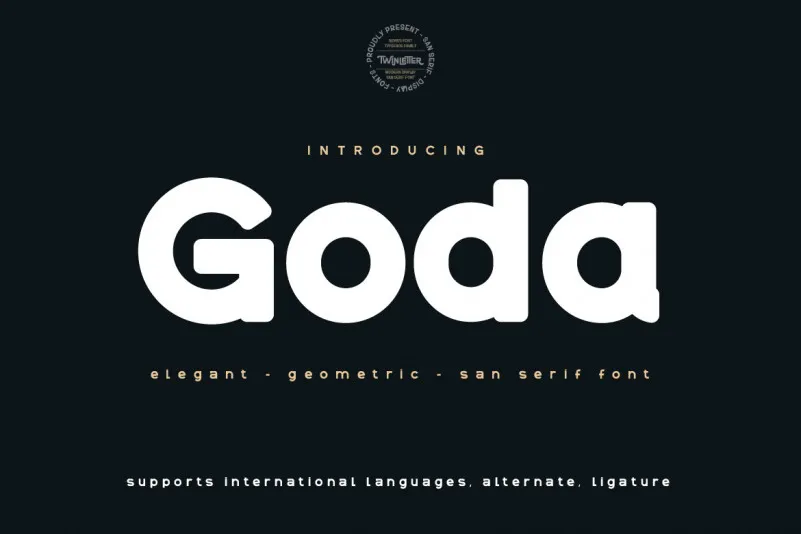
Esta font ‘Goda Sans Serif Font’ é uma peça de arte que combina a beleza suave com a elegância serena para criar um impacto irresistível em qualquer projeto. Seu design delicado e sofisticado permite que você use o mesmo elemento de estilo tanto em projetos masculinos quanto femininos, criando uma harmonia única e versátil. Seja para um site de moda ou uma linha de cosméticos, a ‘Goda Sans Serif Font’ oferece uma maneira perfeita de expressar sua identidade visual de forma elegante e contemporânea.